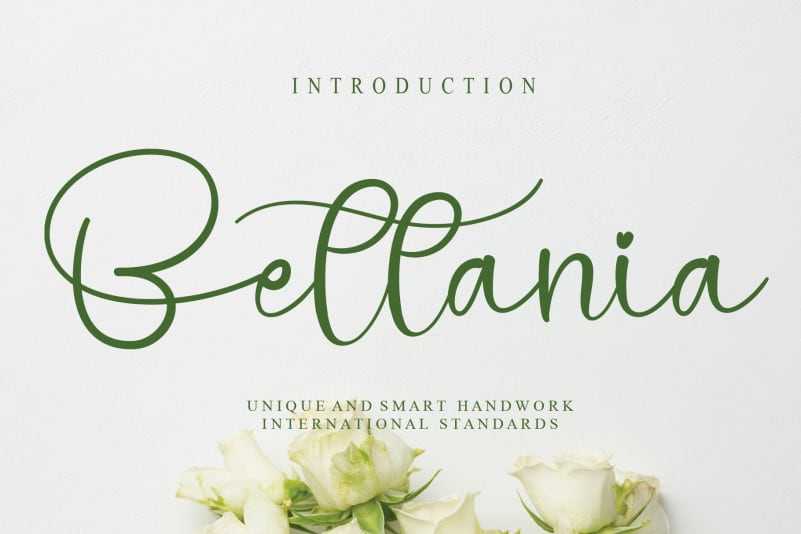
Bettania Calligraphy Font – Download Grátis
A Bettania Calligraphy Font é uma deliciosa escolha para quem deseja trazer uma sensação elegante e autêntica a seus projetos digitais. Embora não tenhamos acesso às características específicas de cada letra, o designer criativo, CreativeLetter, sabe que esta fonte oferece um toque personalizado que transforma qualquer texto em obras de arte. Seja para cartões de aniversário delicadamente decorados, mensagens emocionantes no seu blog ou até mesmo as mais belas listas de compras da sua padaria, a Bettania Calligraphy Font vai fornecer aos designers uma experiência única e especial. Com uma escrita fluida e detalhada, esta fonte é perfeita para quem valoriza cada letra, criando mensagens de verdade com cores que chamam atenção. Inspirado no estilo elegante das caligrafias tradicionais, a Bettania Calligraphy Font oferece uma opção versátil e incrivelmente detalhada. É ideal para projetos onde você deseja um toque personalizado e sofisticado, proporcionando à sua produção o brilho apropriado. Experimente esta fonte; ela certamente dará seu trabalho de arte um toque que tornará sua obra uma lembrança memorável.